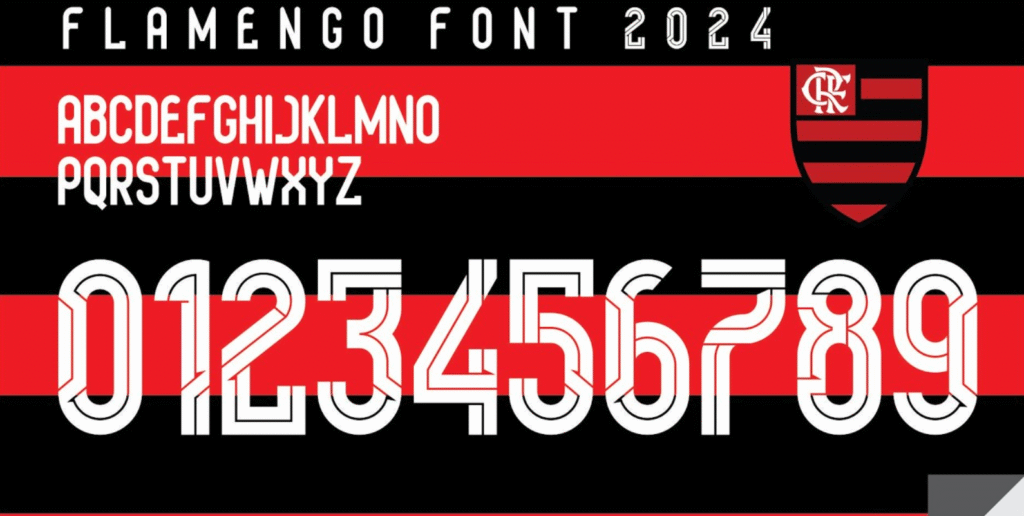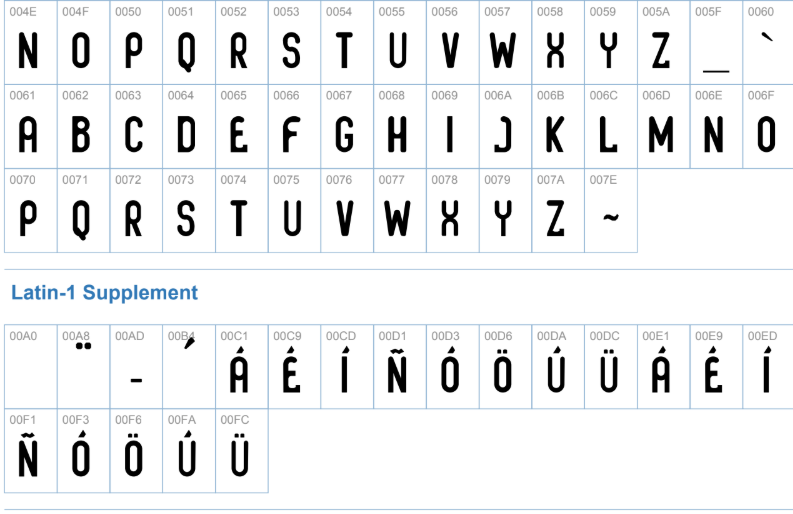
Fonte do Flamengo 2024 TTF: Baixe Agora a Tipografia Oficial da Adidas para o Manto Sagrado
A temporada 2024 do Flamengo já está marcada na história, e cada detalhe do Manto Sagrado conta. A Adidas, fornecedora oficial do clube, desenvolveu uma tipografia exclusiva que estampa os nomes e números dos craques nos gramados. Essa fonte é mais do que um simples design; ela carrega o peso da Nação Rubro-Negra e a identidade visual de um dos clubes mais vitoriosos do mundo.
🎨 Estilo Visual: A Força do Rubro-Negro
A fonte do Flamengo 2024, assinada pela Adidas, foi desenhada com um objetivo claro: modernidade e impacto. Ela apresenta linhas robustas, cantos ligeiramente angulares e uma estrutura condensada, o que garante excelente legibilidade tanto na TV quanto nas arquibancadas.
Diferente de fontes mais arredondadas do passado, este design transmite uma sensação de força, velocidade e precisão. É a tipografia que você vê nas costas de ídolos como Arrascaeta, Pedro e Gabi, estampada nos uniformes principais (Rubro-Negro) e de visitante da temporada.